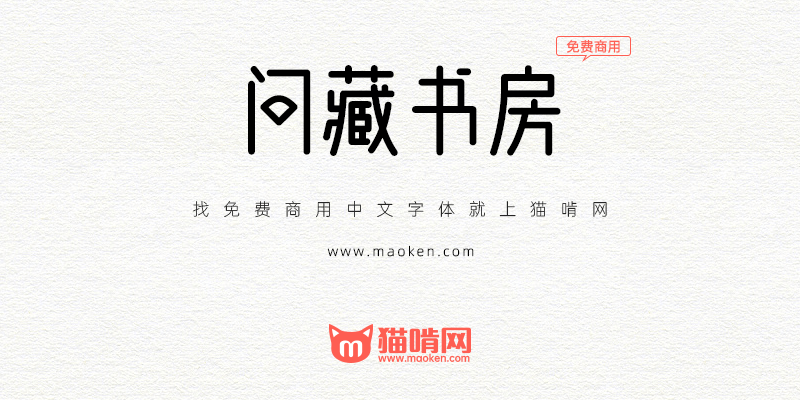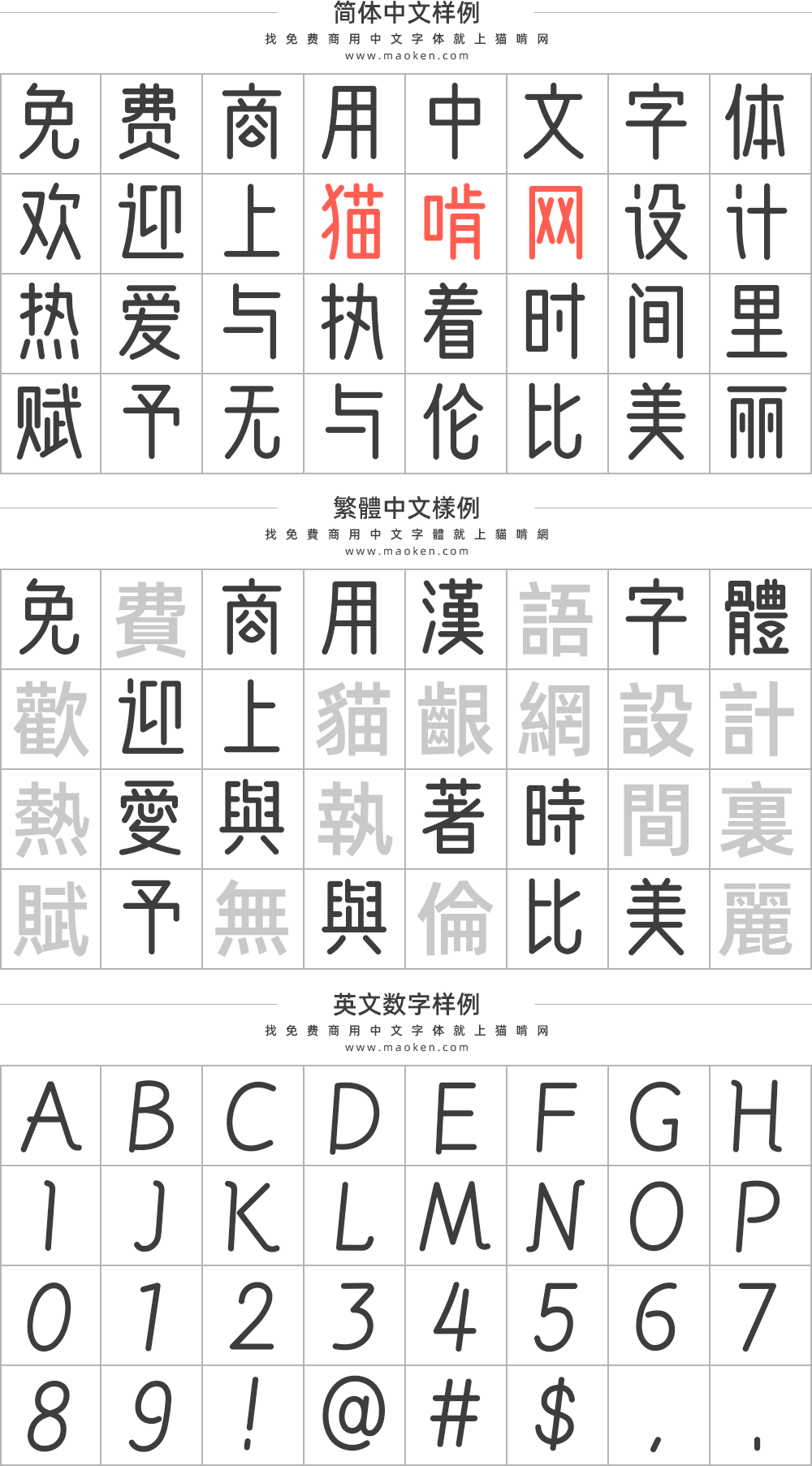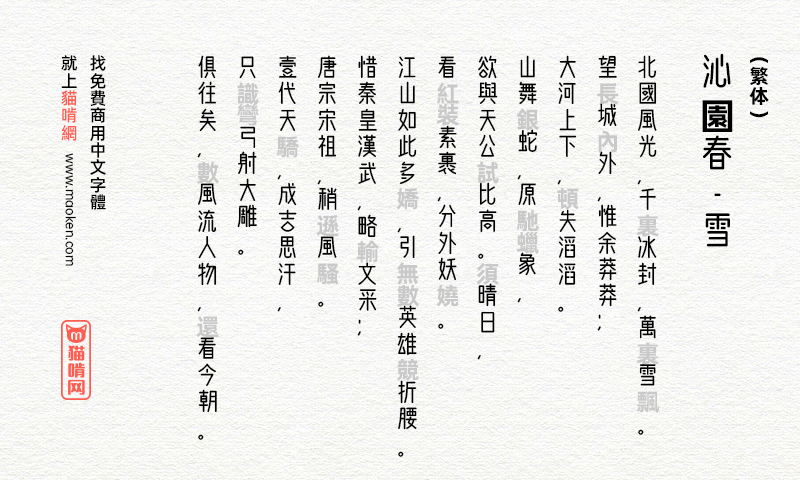
问藏书房:造字工坊为问藏书房定制的品牌字体
问藏书房是造字工房创始人丁一将二十余年收藏和学习的数千本设计、绘画、摄影、字体等艺术图书全部捐助于问藏书房而创建。意向通过问藏书房免费借阅给对设计与艺术、美学类相关知识有兴趣的同学。在各界朋友的帮助和造字工房创新资金全力支持下,投入数百万元,将艺术与美学类书籍的藏书量增至万余册,一并无偿开放借阅给热爱书籍、对审美有更高需求的朋友们,以实际行动为中国的审美教育贡献一份绵薄之力!
适逢中华人民共和国成立七十周年,问藏书房联合造字工房一起,以始终如一的原创精神,精心打造了一款字体产品“问藏书房”字体,在举国同庆之际,开源给中国大陆地区一切个人与商业机构免费使用,以感谢国家给予的所有权益政策,感恩回馈一路支持正版字体的客户和朋友!
问藏书房字体的设计整体现代简约,中宫紧凑,视觉阅读极具层次感,字字俊秀且呈现古雅之风,设计团队以精心的设计赋予了汉字全新美感!字符编码采用中华人民共和国GB2312-80字符集标准,按需添加101个汉字。共收容字数6864CJK汉字,ASCII常用字符100个。